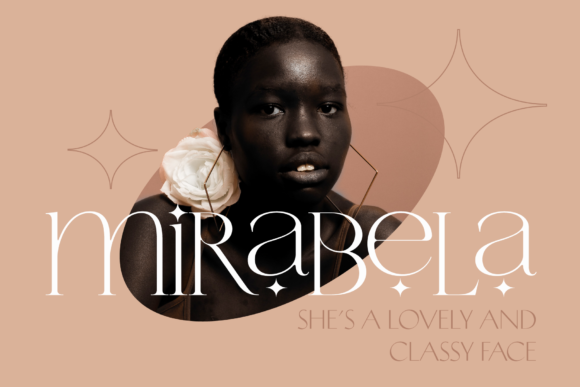
Creativefabrica Mirabela Font
[Creativefabrica] Mirabela Font
Мирабела - элегантный и стильный шрифт с засечкой.
Влюбитесь в его невероятно универсальный стиль и используйте его для создания великолепных приглашений, красивого стационарного искусства, привлекательных сообщений в социальных сетях и многого другого!